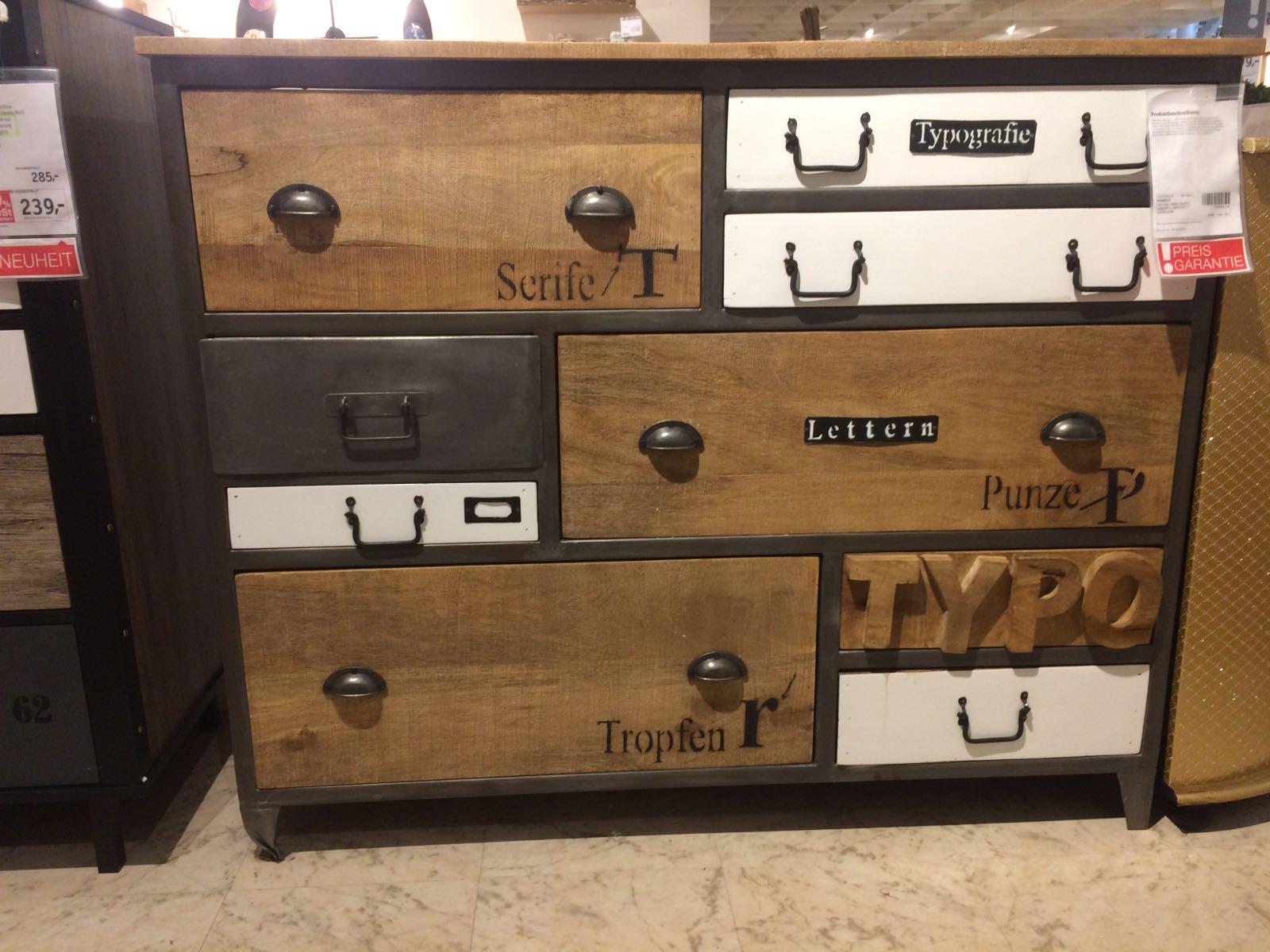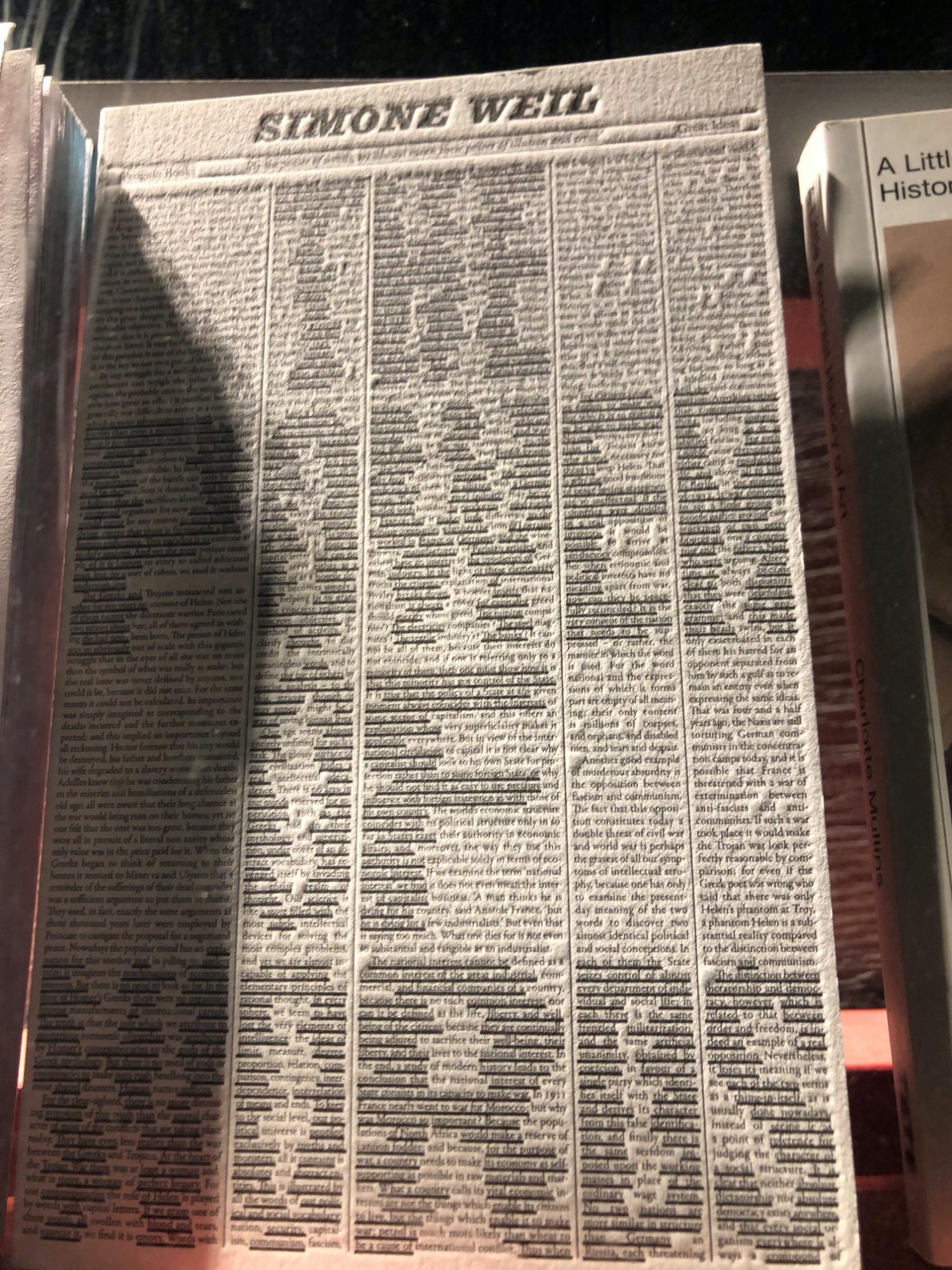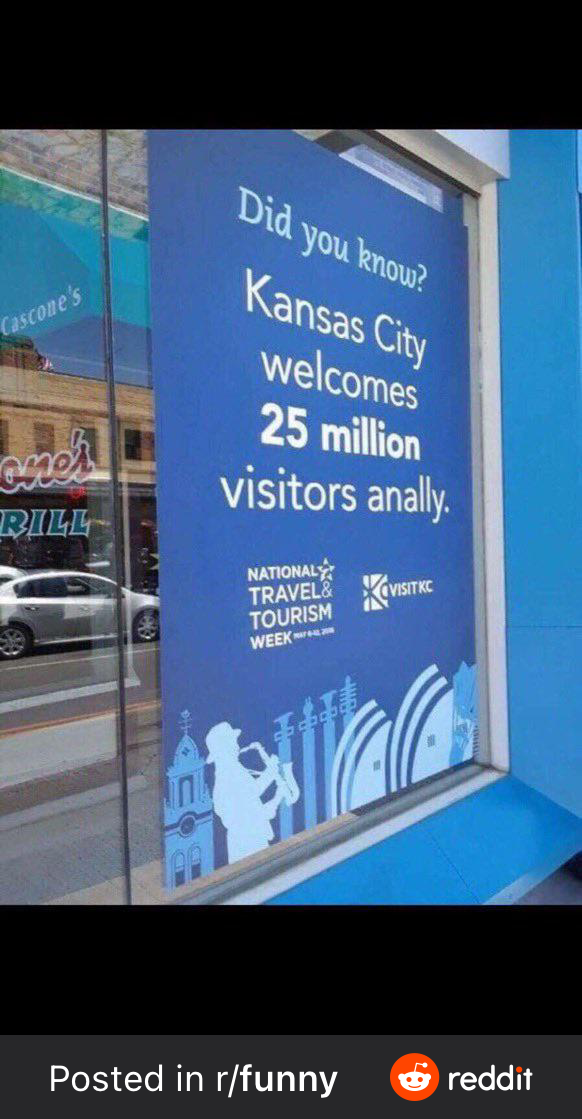
Interessant! Bei mir wenn überhaupt dann »Geniefzen«. Aber bisher kam mir das bei dieser Schrift ehrlicherweise gar nicht in den Sinn. :shock:
Im Gegenteil, ich fand das formale Zusammenspiel zwischen ß und ẞ eher – klasse. :roll:
Aber das ist nur meine Stimme. Wäre wie immer spannend wie das die anderen noch sehen.
So einzeln gesehen finde ich das ß etwas eigenartig, im Satz finde ich es aber gut. Der formale Zusammenhang zwischen Versal und Gemeinem ist ja oft kaum bis gar nicht gegeben*, hier aber gut gelöst. Viele ẞ-Formen finde ich spitz und kantig, diese hier sehr weich und modern (trotz der Reminiszenz an die 20er) – finde ich gut :nicken: Ich glaube solche gelungenen Formen können ganz guter Einfluss auf Verbreitung und Verwendung des VE sein.
* Was kein Problem ist, da z. B. a und A auch wenig gemein haben.
Im Zusammenhang mit dem Thread zu Ascii-Eva  ist mir eben noch ein Buchtitel eingefallen, über den ich letztes Jahr in Venedig gestolpert bin. Hätte ich gerne angefasst, es sieht so schön flauschig aus.
Was die Großen können, können die Kleinen auch:
Da sehe ich aber schon einen deutlichen Unterschied. :-P
Das hat das Logo richtig nach vorne gebracht – nicht der Strich, aber dass die Rotis ersetzt wurde :hammer:
Was die Großen können, können die Kleinen auch:
Ich finde an dem Relaunch gelungen. Es ist gut, dass man sein Stadtlogo sanft anpasst. Dass die meisten Passanten keinen Unterschied erkennen, halte ich sogar für einen Hinweis auf einen gelungenen Relaunch. Die Rotis wegzulegen ist auch gut, den Strich braucht es tatsächlich nicht.
Ist das nicht mal wieder ein Thema, bei dem sich Leute (künstlich) aufregen, die keine Ahnung haben? Wird nicht erklärt, dass an allen möglichen Ecken des offiziellen Auftritts vereinheitlicht, aufgefrischt und durch den Wechsel der Schriftart auch die Befreiung aus einer alten Lizensierung erreicht wurde? Da sitzt so ein Dienstleister auch eine ganze Weile dran, und so etwas nur an dem einen Strich festmachen zu wollen, ist schon fast boshaft.
(Halb off topic: Ich hatte mal einen Kunden, bei dem ich nur sehr wenig zu beanstanden hatte, daher fanden sich wirklich nur eine Handvoll Anmerkungen im Text. Es war aber eine für ihn sehr wichtige Publikation, daher wären auch die wenigen Schnitzer peinlich gewesen. Er fing dann an, herumzudiskutieren, sodass ich klarstellen musste, dass ich keine "Fehlerprovision" bekomme, sondern ein vertraglich vereinbartes Honorar. Pffft.)
ist schon fast boshaft
Und die Leute vom öffentlich-rechtlichen Fernsehen machen sich auch noch zum Instrument dieses gefährlichen Halbwissens und schießen da einfach mal ganz ungeniert gegen die deutsche Kreativwirtschaft, die noch immer und gerade auf dem eher provinziellen Terrain ziemliche Schwierigkeiten hat das Image vom nicht vertrauenswürdigen Werbeheini-Zirkus loszuwerden, von unterirdischen Budgets mal ganz zu Schweigen – so jedenfalls meine Erfahrung bei ähnlich gelagerten Corporate-Design-Projekten. 🤦🏼‍♂️
(Cool, dass Du standhaft geblieben bist und eine gute Erklärung griffbereit hattest!)
Da kann man aber auch mal souverän reagieren und es mit einem Augenzwinkern wegstecken wenn eine Arbeit von Kolleg:Innen mal Gegenstand eines satirischen Beitrags ist. Gefährlicher als derart Halbwissen ist für mich, wenn man Halbwissen auf diesem Gebiet als "gefärlich" tituliert. Wie gefährlich Halbwissen tatsächlich sein kann erleben wir ja grad oft genug im Vorbei- respektive Spazierengehen. Und machen wir uns nichts vor: gerade auch Kreative geben oft genug den Klugscheisser und also auch ohne ausreichend Sachkenntnis ihre Statements auch zu fachfremden Themen ab. Für mich als Gestalter ist zudem schon auch die Spontanreaktion derer, an die ein Entwurf ja auch adressiert ist, interessant, auch wenn diese keinerlei Detaillekenntnis darüber haben.
Gefährlicher als derart Halbwissen ist für mich, wenn man Halbwissen auf diesem Gebiet als "gefärlich" tituliert.
Einverstanden: »Gefährlich« war etwas überzogen.
Da kann man aber auch mal souverän reagieren und es mit einem Augenzwinkern wegstecken wenn eine Arbeit von Kolleg:Innen mal Gegenstand eines satirischen Beitrags ist.
Das war auch nicht das Thema, sondern:
und so etwas nur an dem einen Strich festmachen zu wollen, ist schon fast boshaft.
Ich finde es schon ärgerlich, wenn unzähligen Leuten im Fernsehen weißgemacht wird, dass nur das Weglassen eines Striches und die Anpassung einer Schriftart 9.000 € gekostet hat. Es stimmt einfach nicht und wirft in dem Zusammenhang ein völlig falsches Licht auf die Branche. (Mit Verhaltensweisen von einzelnen »Kreativen« hat das aus meiner Sicht auch erstmal nichts zu tun.)
Ich fände es auch ärgerlich wäre der Sachverhalt in dieser unvollständigen Form  in "aspekte" so dargestellt.
Aber der Papst, Bernd Höcke oder Cathy Hummels, sie werden in der "heute-show" nunmal anders behandelt als in "heute". Ich denke der überwiegende Teil der Zuseher:Innen weiss das schon korrekt einzuordnen. Ich hab bestimmt schon über Beiträge dort gelacht in der sich "Betroffene" genau so angepisst gefühlt haben wie es in diesem Fall Kreative tun. Und das wahrscheinlich oft genug auch mit deutlicher weniger als nur Halbwissen.
Tippfehler, oder verärgerter Gestalter?
Real or fake? :-?
Zum PCR-Test gibt es gleich eine Colonoskopie und ggf. eine Prostatauntersuchung. Sehr fürsorglicher Staat 😄
Hallo, wer kann mir helfen und mir einen Tipp geben, wo es diese Kommoden (Gutmann Factory) mit den Typografie-Begriffen gibt?